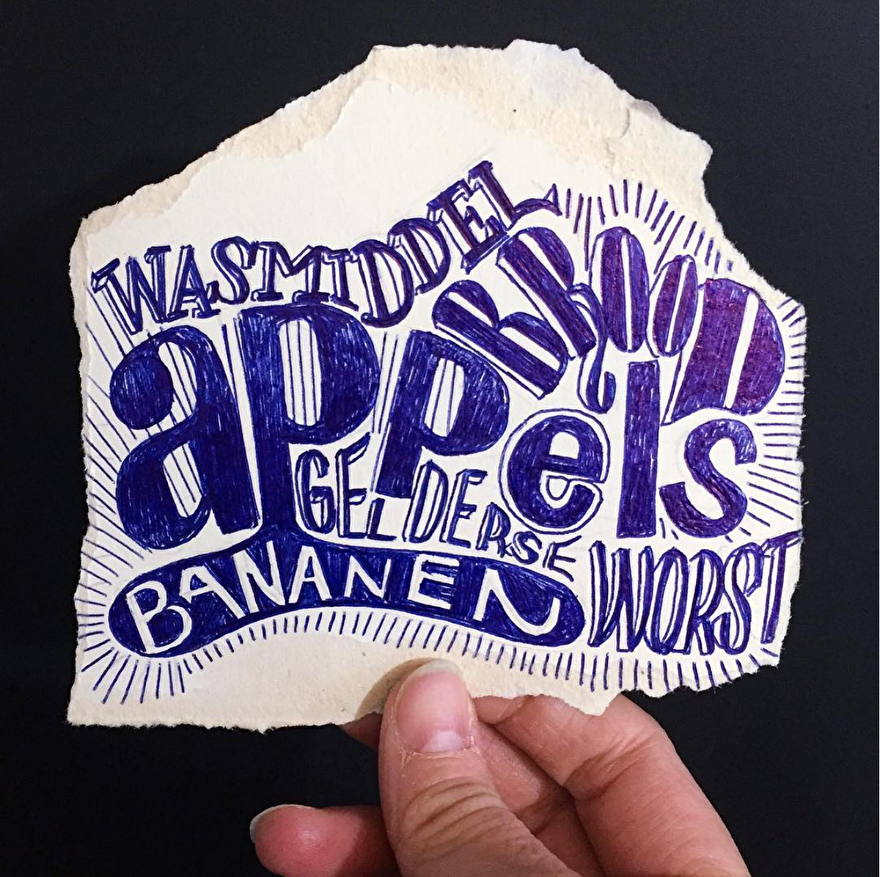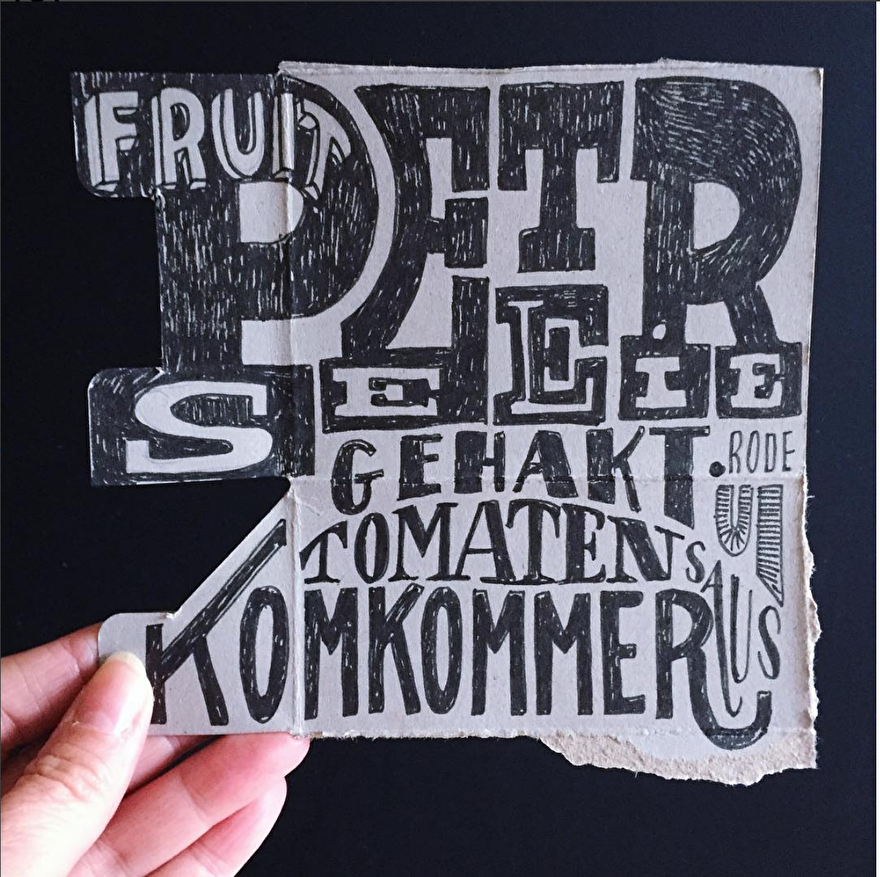
Workshop 'Boodschappenbriefjes'
WORKSHOP BOODSCHAPPENBRIEFJES
AL een paar jaar letter is een paar keer per week mijn boodschappenbriefje.
Dat lijkt misschien onzinnig, want hè, waarom zou je daar nu zoveel tijd aan besteden. Ten eerste valt het heel erg mee qua tijd (gemiddeld doe ik over een briefje rond de 15 minuten). Maar daarnaast is het eigenlijk een perfect middel om je handletteren te oefenen.
Wil je verschillende letters leren tekenen? Waar moet je op letten en hoe kan je ze samen gebruiken. Graag leg ik je basis uit van hoe van een simpele basisletter een hele andere letter kunt maken. We blijven niet te lang hangen in perfectie, veel oefenen is de beste basis om het te leren. En dat gaan we ook doen in deze workshop. Na de workhsop schrijf je nooit zomaar je naam even op een kaartje ;) In deze workshop gaan we verschillende oefeningen doen waarbij je stap voor stap van basis naar freestylen gaat, perfect om te gebruiken in je dagelijkse leven, in je art journal of in je urban sketchbook.
De kracht van een booschappenbriefje is durven! En daar gaat deze workshop ook over.
'Gewoon doen' klinkt simpel. Maar daarom is het zo fijn om dit in een workshop te doen. Je grens opzoeken, of wellicht eroverheen gaan. Freestylen is voor mij beginnen zonder schets. Je reageert op wat je hebt gedaan. Een mooie manier om ook te leren improviseren. Want als het fout gaat kun je je werk -in plaats van weggooien- een andere wending geven. We hebben allemaal vaak een beeld in ons hoofd als we iets gaan maken. Maar wat gebeurd er als het 'verkeerd gaat' gooi je het dan weg? Durf jij het aan om 'zonder beeld voor ogen' verder te gaan? We gaan stoeien met composities (vlakverdeling), we gaan letters in elkaar over laten lopen, en vooral....gaan we spelen! Weet niet bang, je mag gewoon met een fineliner aan de gang... maar balpennen staan wèl op tafel.
Voor de oefeningen gebruiken we lekkere onzinteksten als boodschappenbriefjes en to do lijstjes. Eigenlijk leent de 'onzin' van de dag zich prima voor deze workshop. Ik leg je graag uit waarom het letteren van deze 'onzin' zo zinvol is. Wat je er van kunt leren zodat je dit overal, met elke quote of in je bulletjournal, kan toepassen.
Moet je een gevorderde handletteraar zijn om mee te doen? Heel veel kennis hebben? Je hoeft geen ervaring te hebben om mee te doen, maar ook als je al wat langer bezig bent met handletteren is het denk ik heel leuk om eens een paar uur te gaan letteren op een hele andere manier. Dàt is zo leuk aan deze workshop: dat je even wordt uitgedaagd het even helemaal anders te doen, of in elk geval te proberen ;)